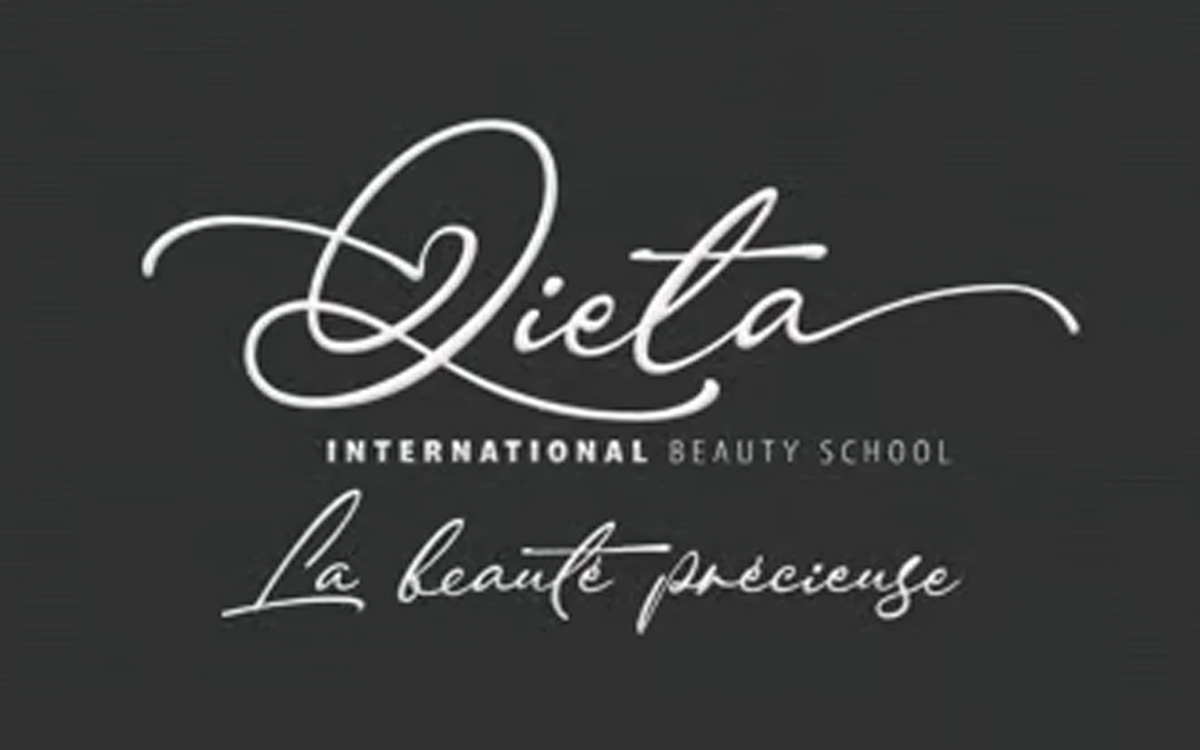
Khám Phá Font Chữ Ký TH Corinthiago Việt Hóa
Khám Phá Font Chữ Ký TH Corinthiago Việt Hóa – Nét Bút Chân Thực & Sang Trọng
TH Corinthiago là một phông chữ ký (signature font) tuyệt đẹp, mang đến cảm giác bay bổng, phóng khoáng nhưng không kém phần thanh lịch. Lấy cảm hứng từ những nét chữ ký viết tay nhanh và tự nhiên, phiên bản Việt hóa hoàn chỉnh của TH Corinthiago sẽ là “vũ khí” đắc lực để nâng tầm các dự án thiết kế của bạn.
✨ Đặc Điểm Nổi Bật Của TH Corinthiago
• Đường nét tự nhiên: Phông chữ mô phỏng hoàn hảo nhịp điệu của một chữ ký thật với các nét thanh, nét đậm chuyển đổi mượt mà, tạo cảm giác cá nhân hóa cao độ.
• Việt hóa chỉn chu: Hệ thống dấu câu tiếng Việt được thêm vào một cách tinh tế, đảm bảo không phá vỡ cấu trúc bay bổng nguyên bản của font chữ. Các dấu được đặt ở vị trí cân đối, tránh tình trạng lỗi hiển thị (kerning) khi gõ các từ phức tạp.
• Ký tự thay thế (Alternates & Ligatures): Hỗ trợ nhiều bộ ký tự nối (ligatures) đẹp mắt, giúp các cụm từ liền nhau trông tự nhiên và nghệ thuật hơn.
🎯 Ứng Dụng Thực Tế
Với phong cách đặc trưng, TH Corinthiago Việt Hóa là lựa chọn hoàn hảo cho các dự án cần điểm nhấn cá nhân và sự sang trọng:
• Thiết kế Logo cá nhân & Watermark: Tạo dấu ấn chuyên nghiệp cho các nhiếp ảnh gia, nhà thiết kế, hoặc các thương hiệu cá nhân (Personal Branding).
• Ấn phẩm cưới hỏi: Mang lại vẻ đẹp lãng mạn cho thiệp mời, phông nền (backdrop) và album ảnh cưới.
• Bao bì & Nhãn hiệu: Rất phù hợp cho các sản phẩm thời trang, mỹ phẩm cao cấp, hoặc nhãn mác cần sự tinh tế.
• Trích dẫn (Quotes) & Social Media: Thổi hồn vào các bài đăng mạng xã hội với những câu trích dẫn mang đậm chất thơ.
💡 Mẹo nhỏ khi sử dụng: Để font chữ ký phát huy tối đa vẻ đẹp, bạn nên sử dụng ở kích thước tương đối lớn và kết hợp cùng một phông chữ Serif hoặc Sans-serif đơn giản (như Montserrat hoặc Roboto) cho phần nội dung phụ. Điều này sẽ tạo ra sự tương phản tuyệt vời và làm nổi bật tiêu đề chính.